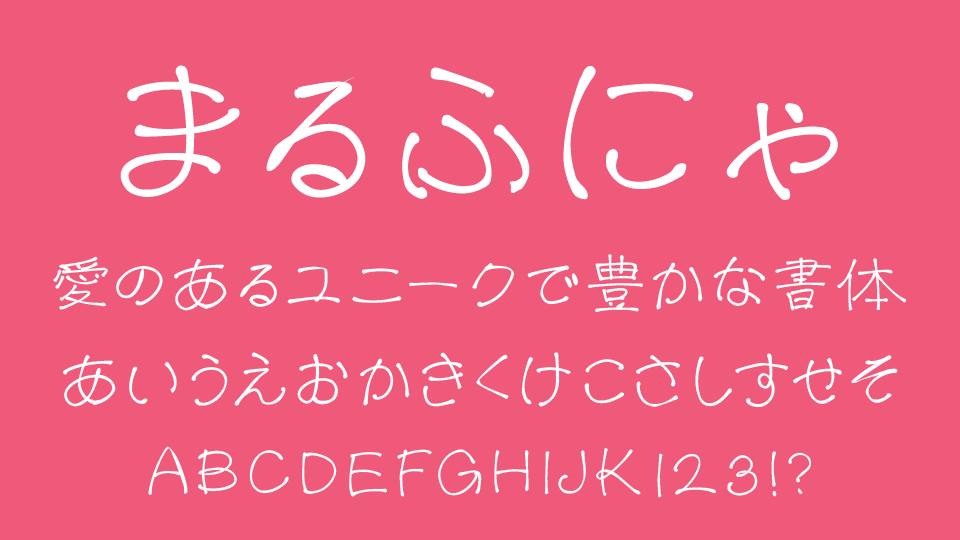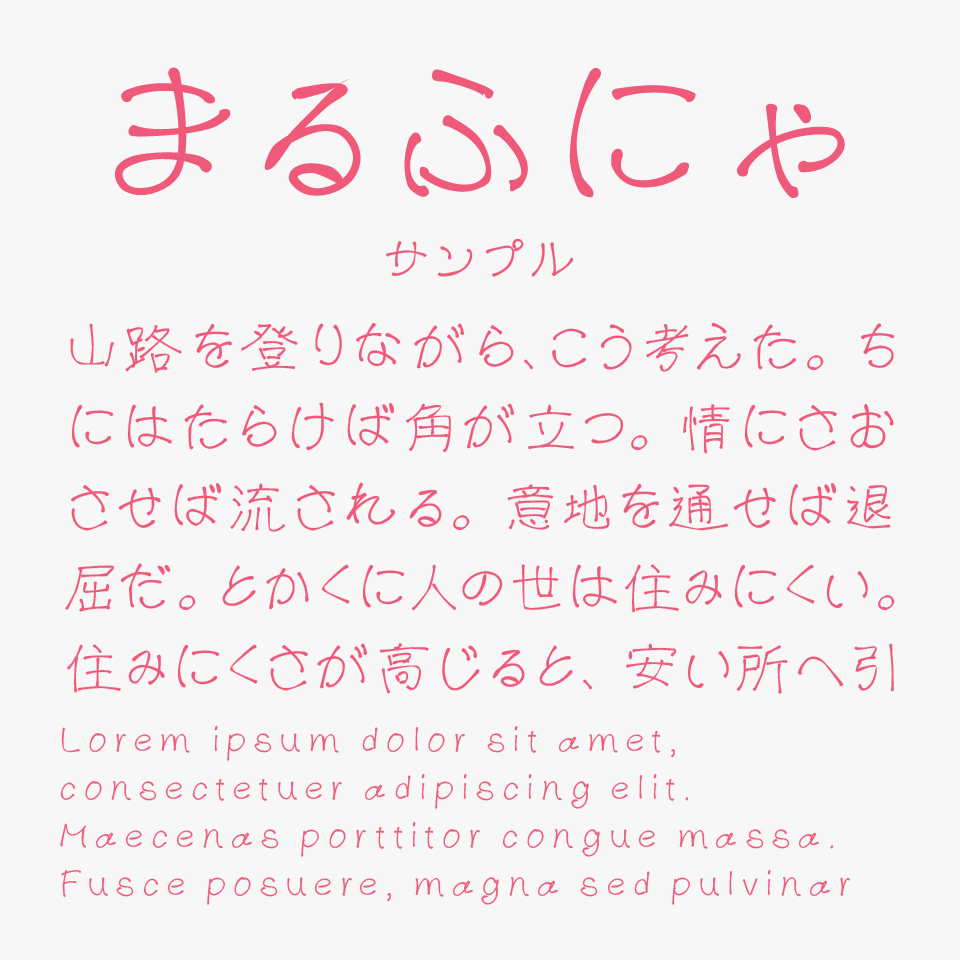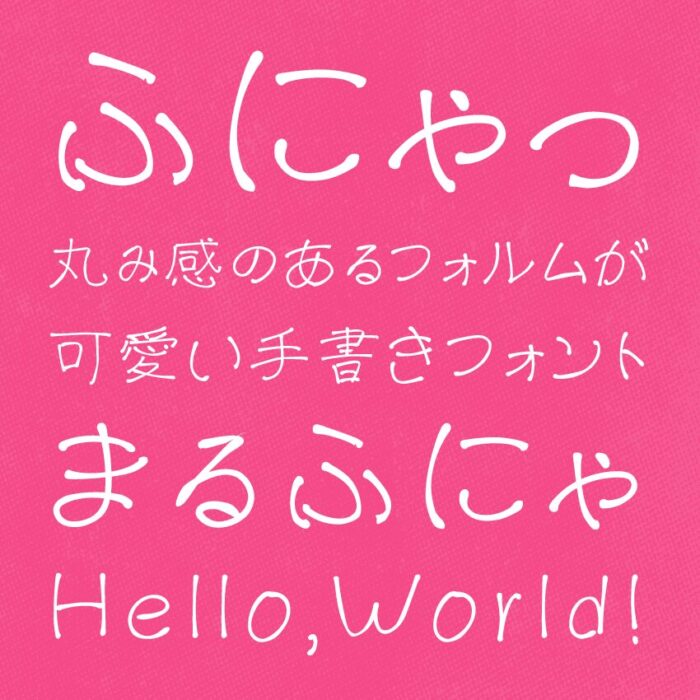
まるふにゃふぉんと
まるふにゃふぉんとは、やわらかい線と丸みを帯びた字形が特徴の、ゆるふわ感あふれる手書きフォントです。
丸みが強くて可愛らしいフォルムと、線先にはインク溜まりや、かすかに揺れたような筆致が、リアルな手書き質感となっていて、かわいらしい雰囲気のある手書きフォントです。
ふにゃっとした丸みがとっても可愛い手書き文字です。